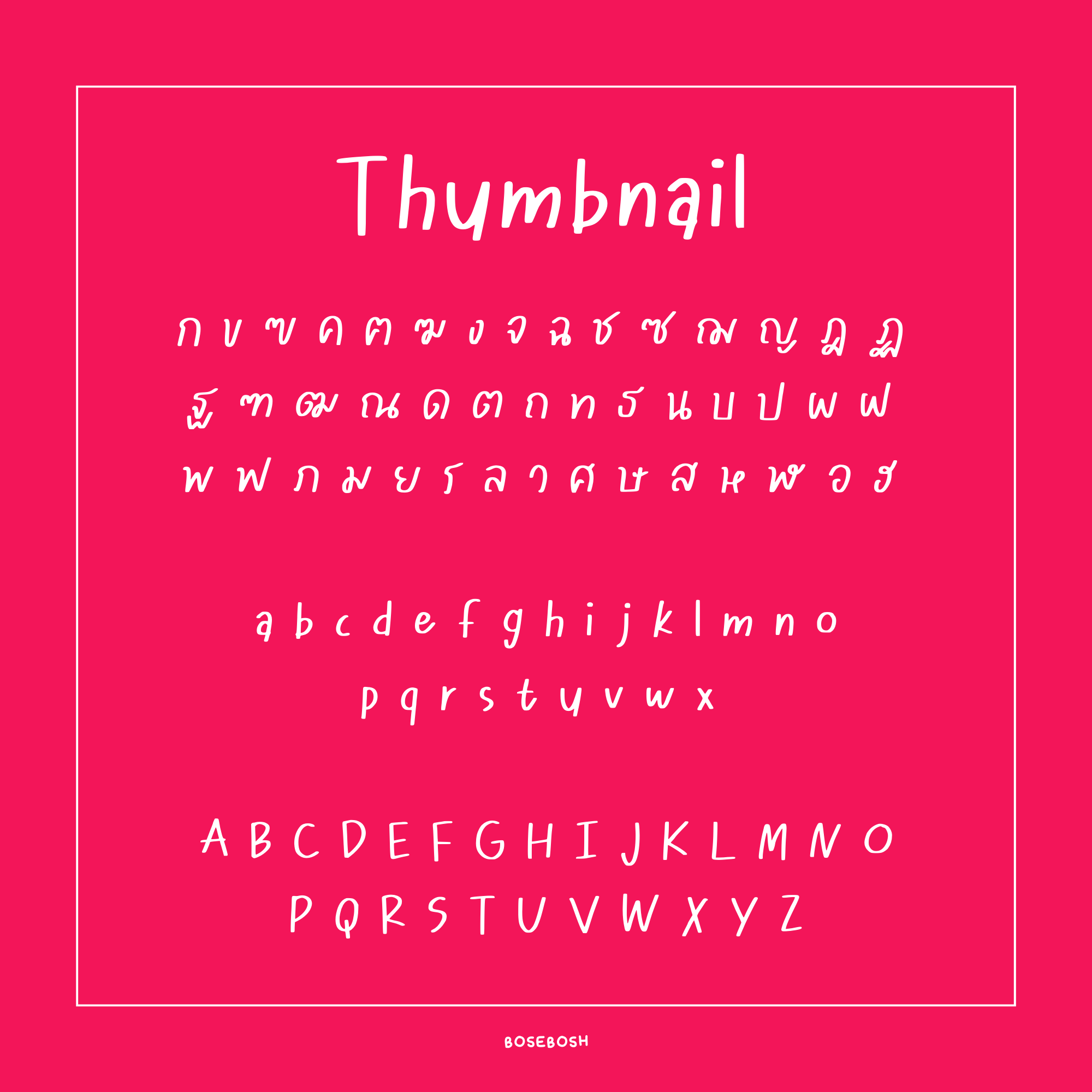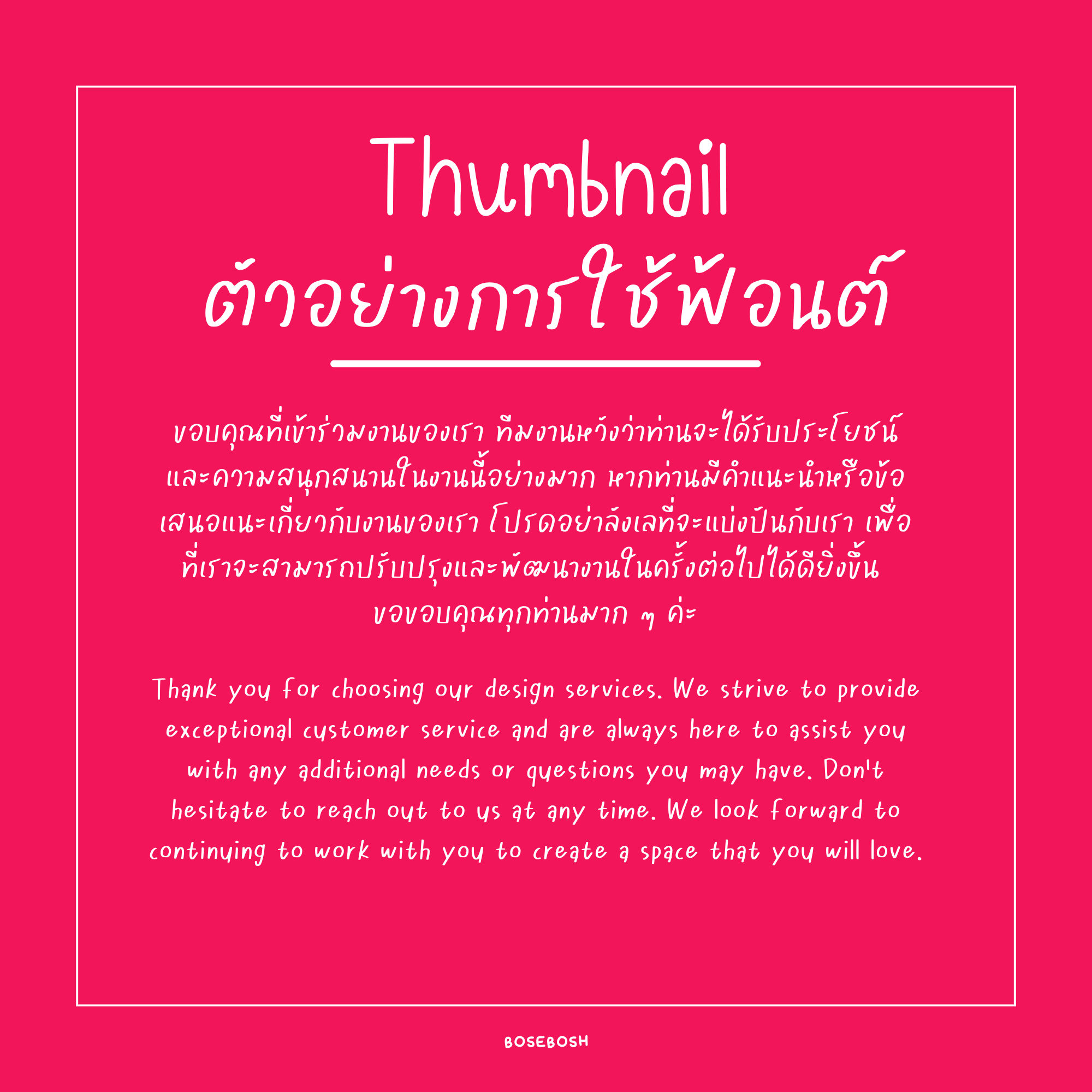
Thumbnail Font
✏️ Thumbnail — ฟอนต์ลายมือเรียวสวย เส้นพริ้ว ตัวกว้างนิด ๆ เหมาะกับการใช้ทำภาพหน้าปกหรือแบนเนอร์
🎯 รองรับไทย อังกฤษ ตัวเลข สระไม่ทับกัน อ่านง่ายแม้ขนาดเล็ก
💡 เหมาะกับการทำ thumbnail YouTube, คำโปรยในงานกราฟิก, วิดีโอรีวิว
🌟 ฟอนต์ลายมือสุดน่ารัก พร้อมใช้งานได้สารพัด! ✨
🎀 ไม่ว่าจะใช้จดโน้ต เขียนสรุป ทำโปสเตอร์ ตกแต่งสไลด์ ทำปก หรือใส่ข้อความในวิดีโอ ก็ช่วยเพิ่มความสดใสได้ในทันที!
🖋️ ถูกออกแบบให้เหมือนลายมือจริง อ่านง่าย สบายตา
🔠 รองรับทั้งภาษาไทย ภาษาอังกฤษ ตัวเลขอารบิก และเลขไทย
❤️ ฟอนต์เดียว ครบ จบทุกงานสร้างสรรค์